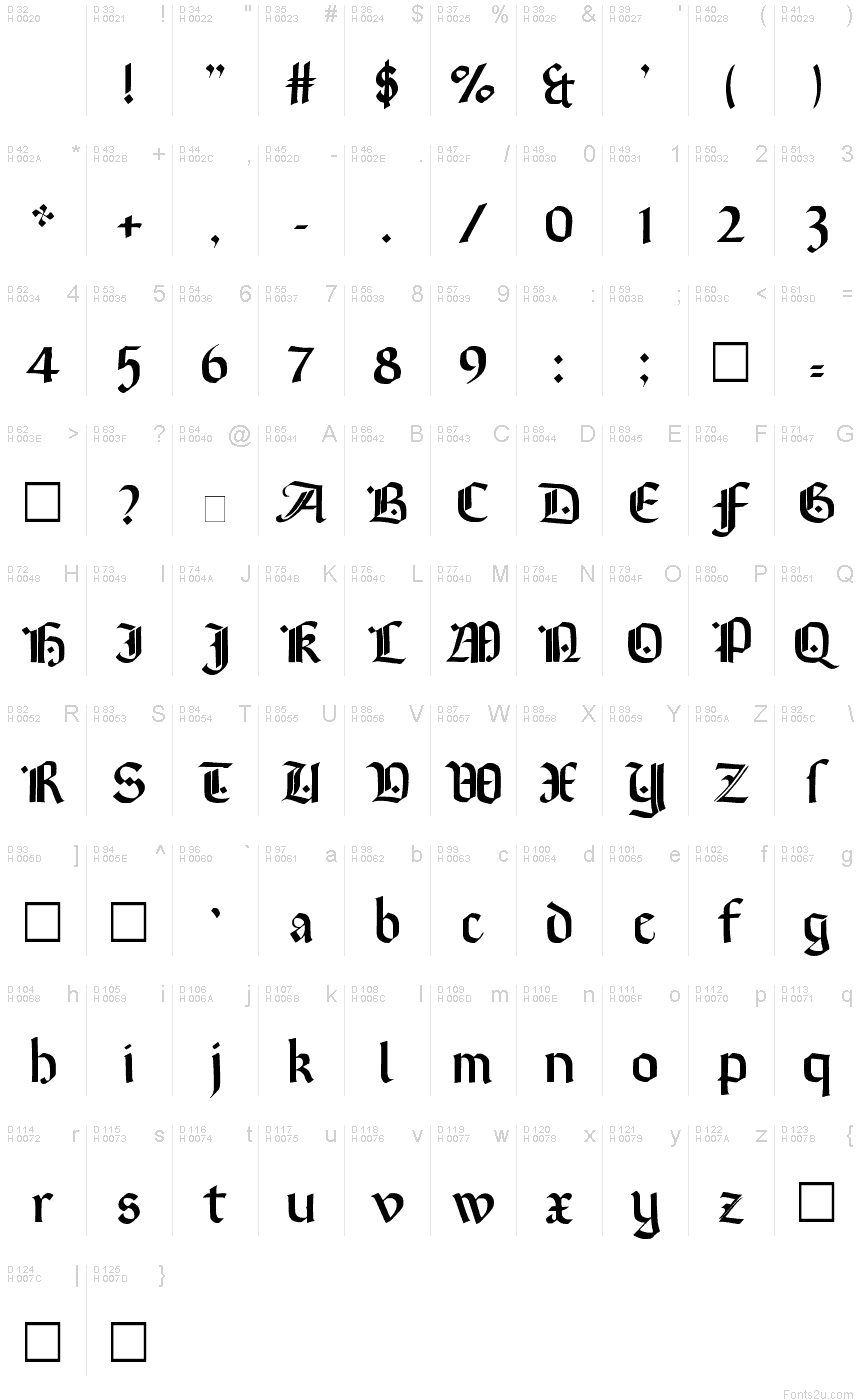
Brinkmann AH von Andreas Höfeld ist eine kostenlose mittelalterliche gotische Schrift. Schwere, mit Tinte getränkte Striche und scharf gefaltete Kurven verleihen ihr die dunkle Dramatik alter Kirchenfenster, während die kompakte Laufweite die Worte zu einem massiven, gemeißelten Textband verdichtet. Es wirkt, als wäre die Schrift in Metall gestanzt oder in Leder geprägt worden, wodurch jedes Wort eine gewisse Schwere und Entschlossenheit erhält.
Mit Brinkmann AH gewinnen Titel und Logos für Fantasy-Romane, RPG-Kampagnen, Metal-Bands, Bieretiketten, Tattoo-Vorlagen und Plakate für historische Veranstaltungen sofort eine düstere, altertümliche Präsenz. Diese kostenlose Schrift kommt in großen Größen am besten zur Geltung, wo ihre kunstvollen Formen ihre volle Wirkung entfalten können; kombinieren Sie sie für den Fließtext mit einer schlichten, modernen serifenlosen Schrift, um die Lesbarkeit und Bodenhaftung des Layouts zu gewährleisten.
A calligraphic display font for certificates, invitations, old-fashioned posters etc. Its style loosely follows the Italo-Spanish Rotunda of the 14th/15th c.